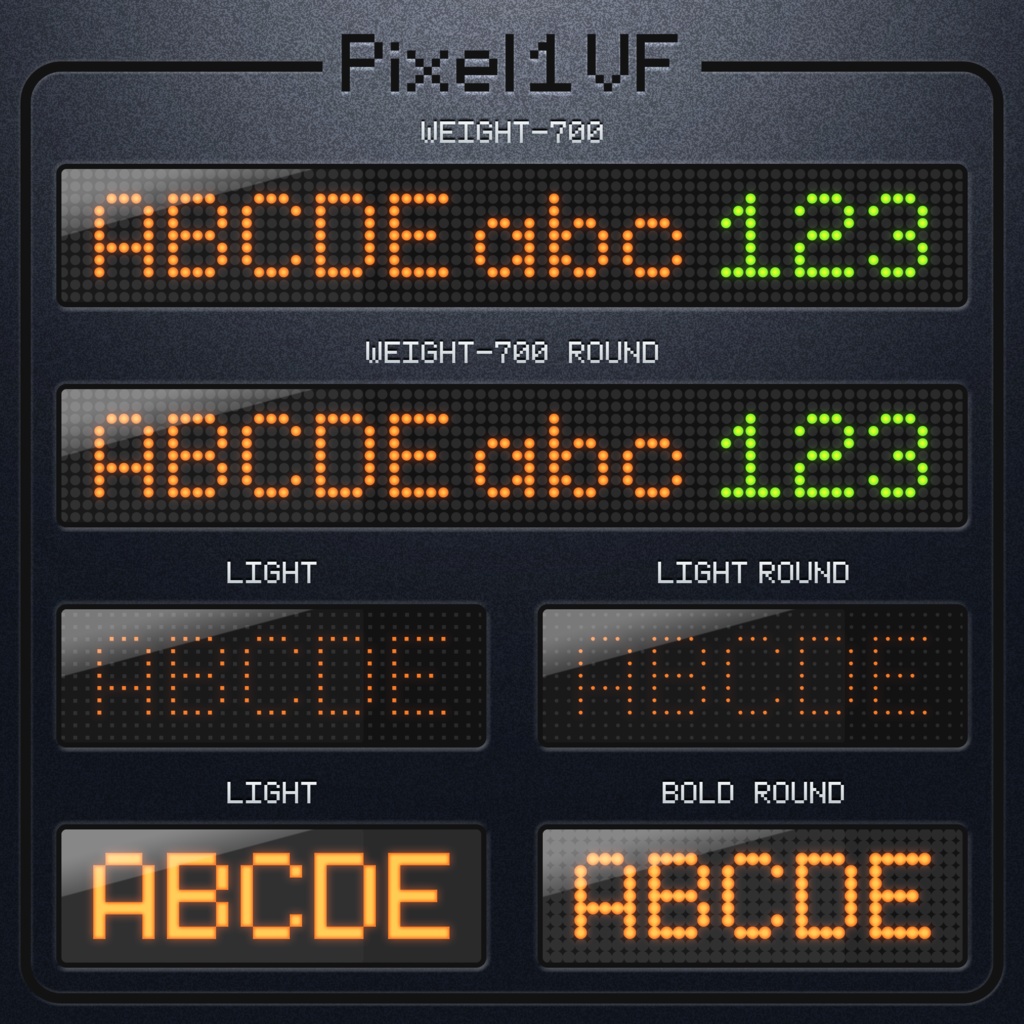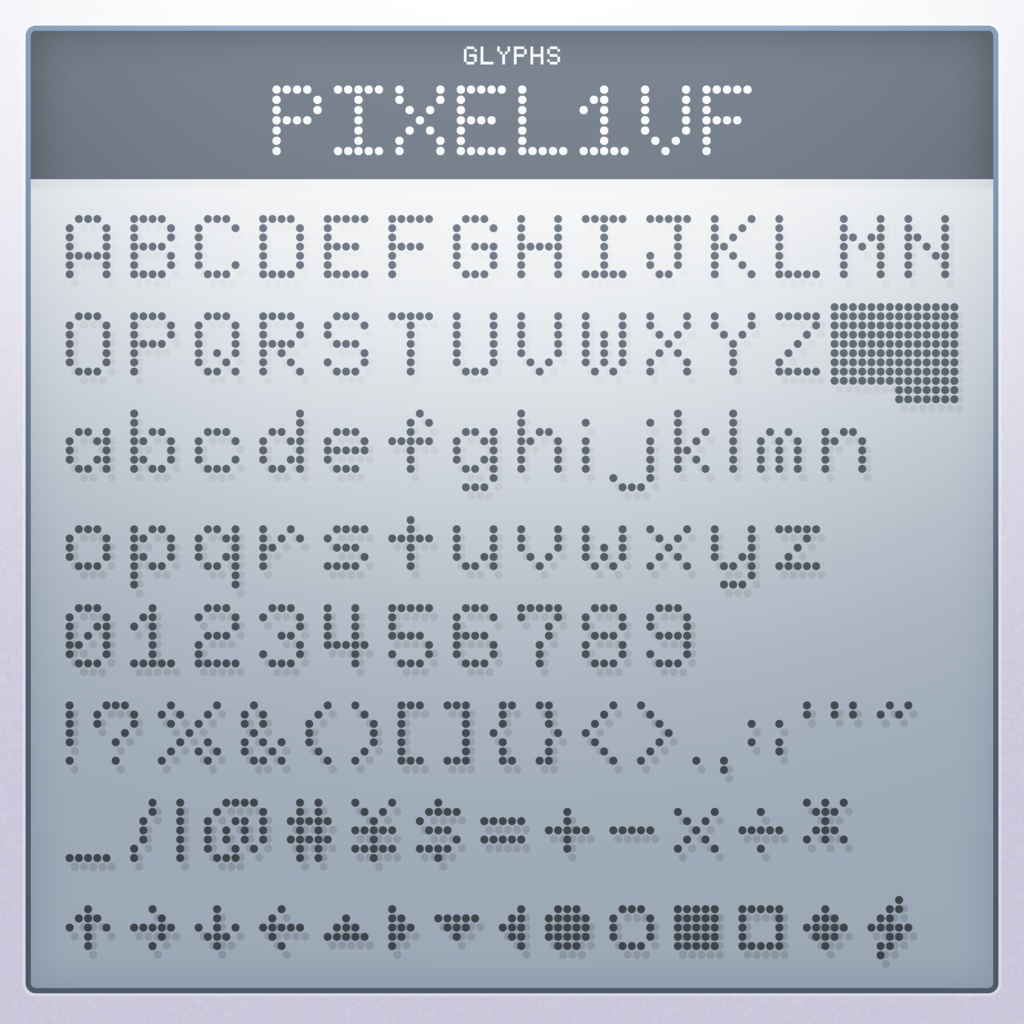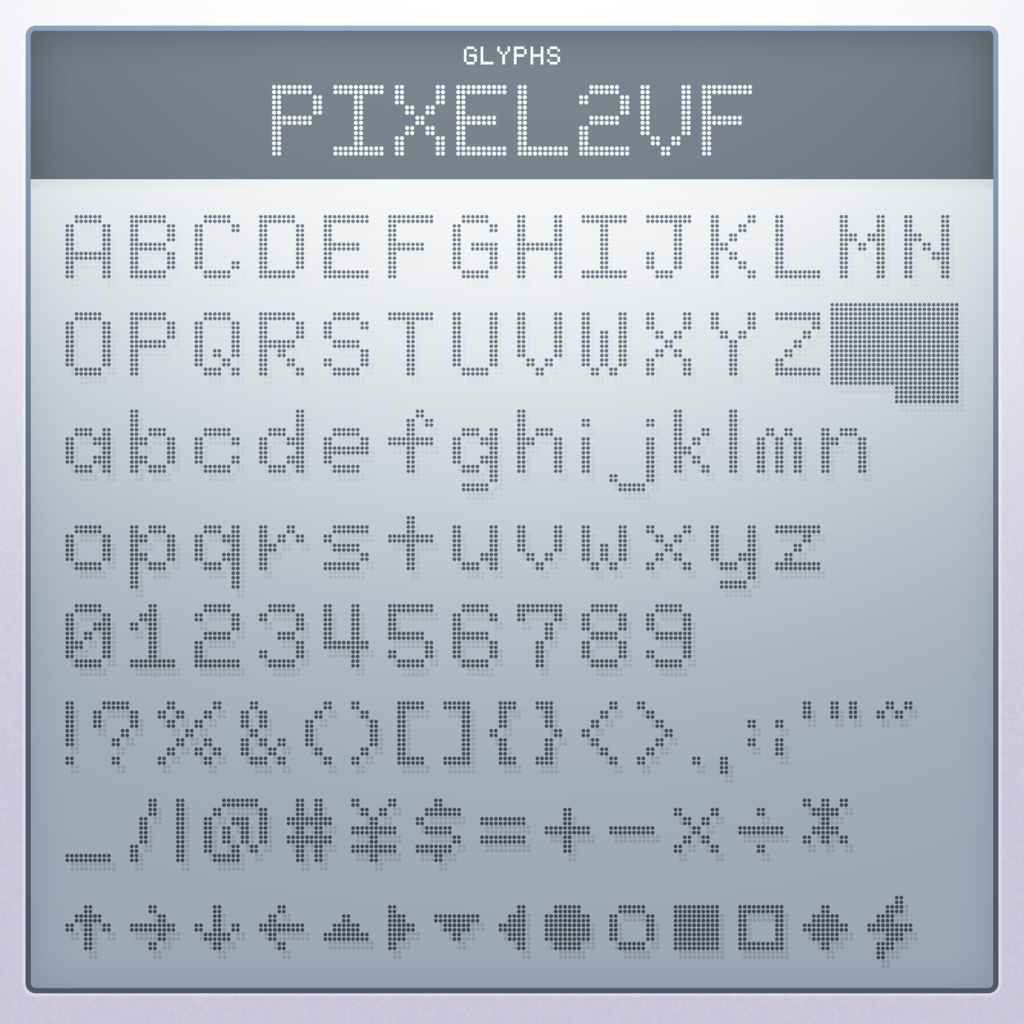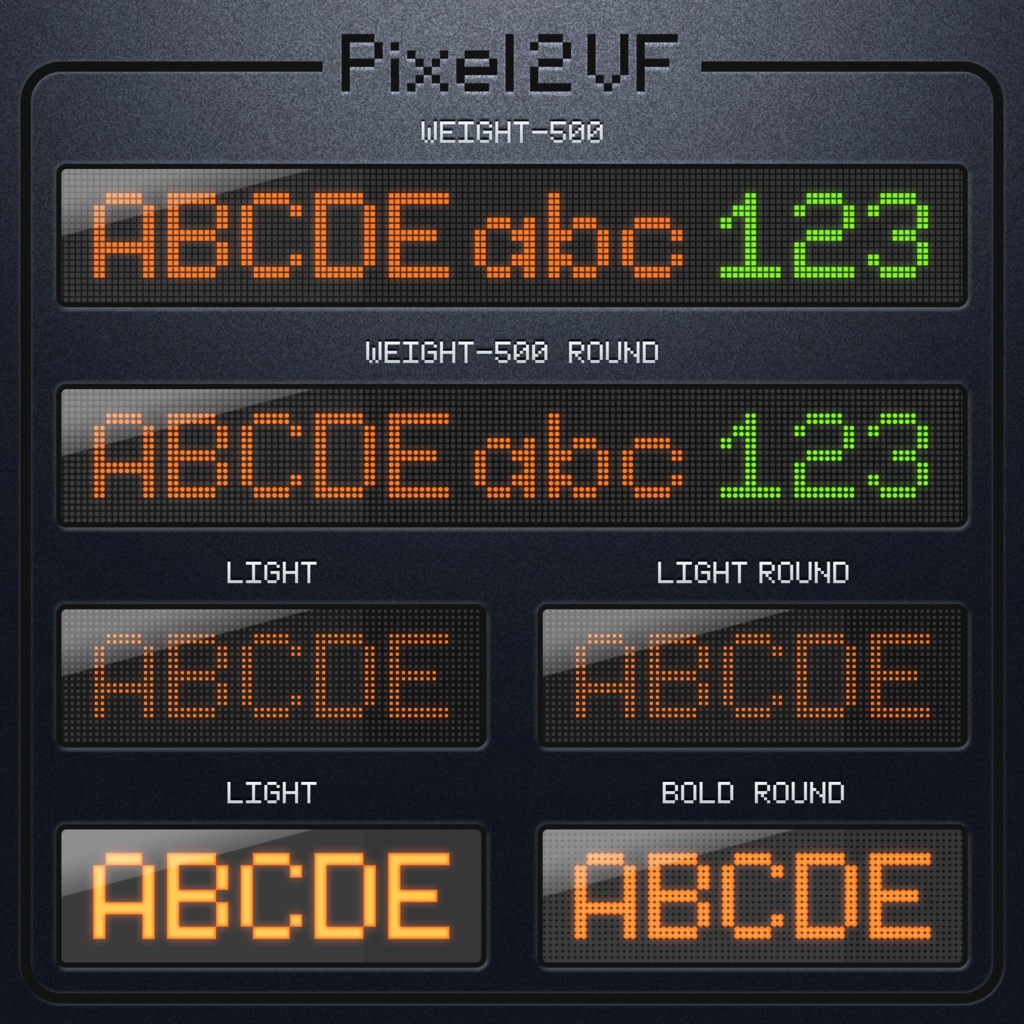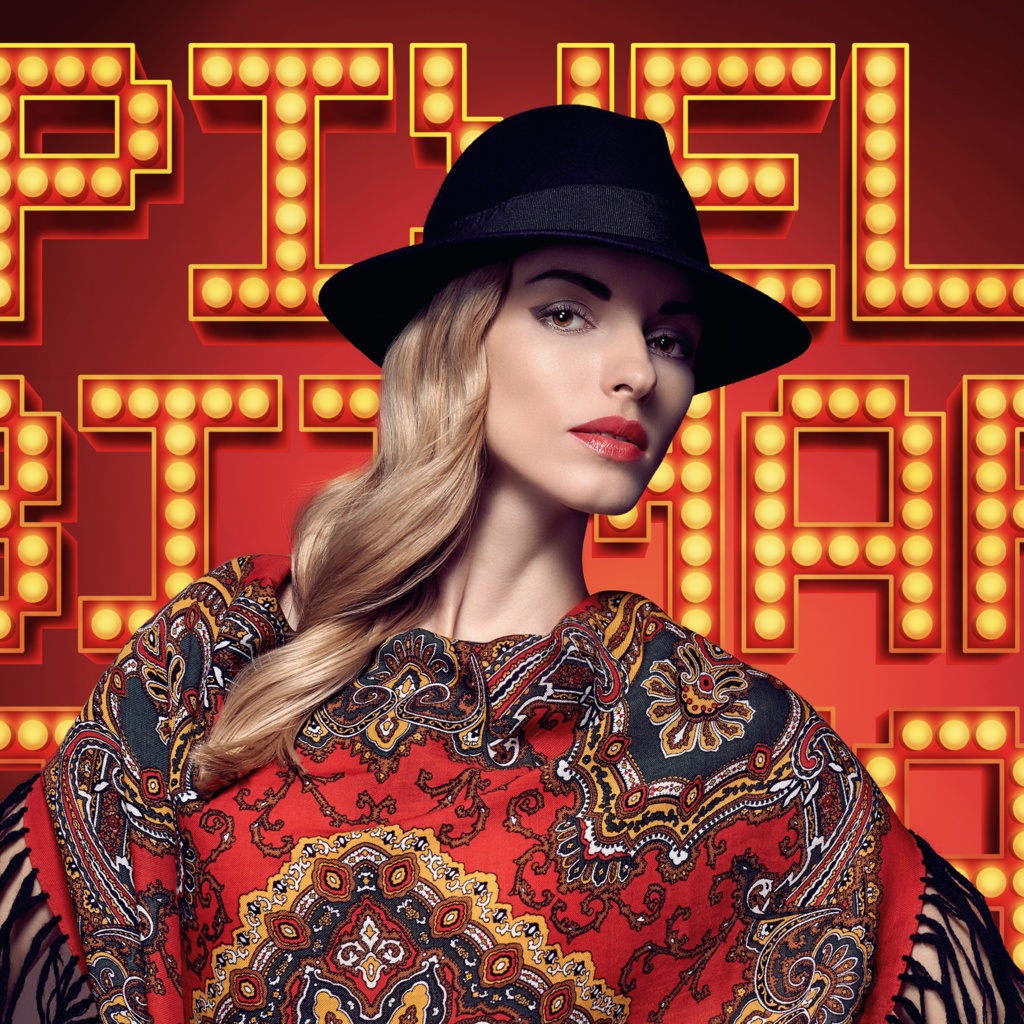
ドット(ピクセル)のバリアブルフォント/PIXELVF
PIXELVFはドットフォント(ピクセルフォント)のバリアブルフォントです。 デジタル表示や近未来風、ゲームデザイン等さまざまなコンテンツにマッチします! ウェイトとRの二軸が可変なのでデザインのテイストに合わせてご使用ください。 英語の大文字・小文字、数字、約物、記号を収録しております。 PIXEL1は主に5x7のブロックで構成、PIXEL2はPIXEL1を分割して主に10x14のブロックで構成しております。 気に入っていただけたらスキ!を押していただけると嬉しいです。 励みになります!
バリアブルフォントとは?
字形の表示方法